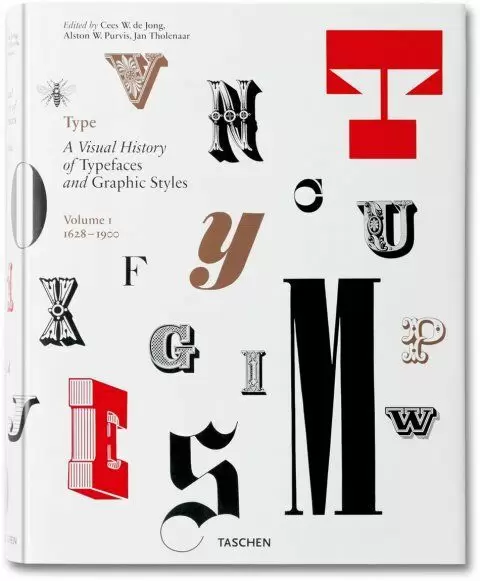
TYPE. A VISUAL HISTORY OF TYPEFACES & GRAPHIC STYLES. 1628?1900
THOLENAAR, JAN / PURVIS, ALSTON W.
Una historia visual de fuentes y estilos gráficos, volumen 1: 1628–1900
Esta selección exuberante de fuentes y estilos tipográficos traza la evolución moderna de la letra impresa, reproduciendo páginas de catálogos exquisitamente diseñados que muestran familias de caracteres en redonda, cursiva, negrita, seminegrita, compacta y ancha. También contiene filetes, florituras, capitulares y otros ornamentos, así como muchos ejemplos deslumbrantes de su uso. Las fuentes victorianas, espectaculares por su complejidad, ocupan un lugar prominente. Además, se incluyen y describen ejemplos de litografía y letras por grabadores y calígrafos.
El volumen presenta obras de los diseñadores tipográficos William Caslon, Fritz Helmuth Ehmcke, Peter Behrens, Rudolf Koch, Eric Gill, Jan van Krimpen, Paul Renner, Jan Tschichold, A. M. Cassandre, Aldo Novarese y Adrian Frutiger.
Para dar cabida a un material tan amplio, hemos dividido los contenidos en dos tomos. Éste, el primer volumen, abarca muestras tipográficas previas al siglo XX, con textos por el editor Cees de Jong y el collecionista Jan Tholenaar.